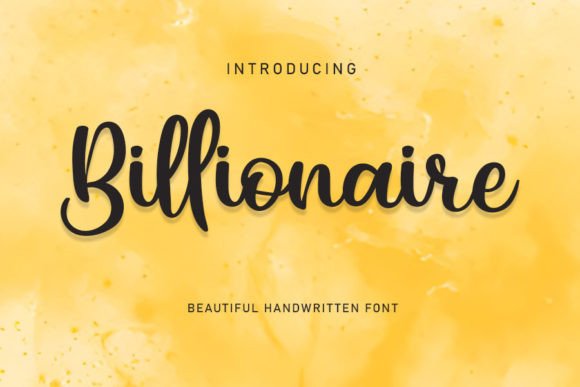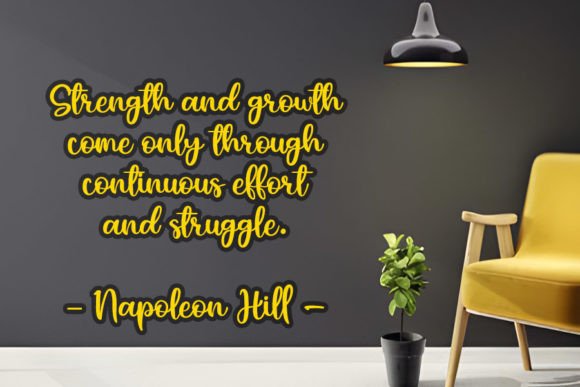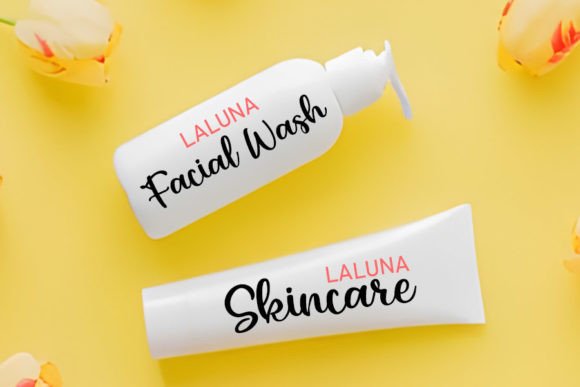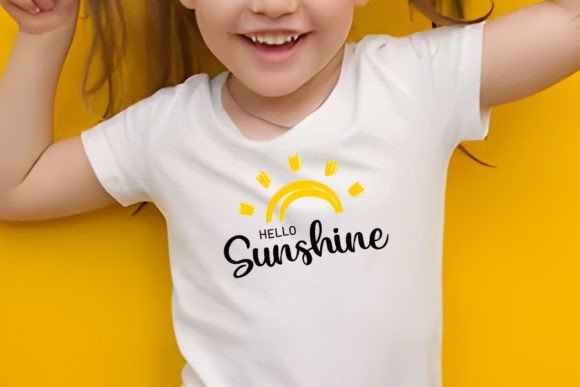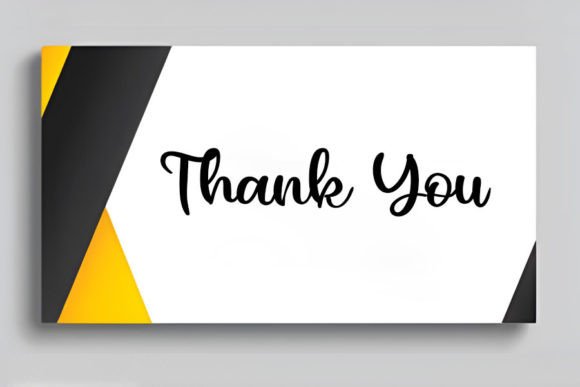
فونت Billionaire انگلیسی
| ⭐ توضیحات | Billionaire یک فونت دست نویس فوق العاده منحصر به فرد است. این فونت که استادانه طراحی شده است تا به یک مورد علاقه واقعی تبدیل شود، این پتانسیل را دارد که هر یک از ایده های خلاقانه شما را به بالاترین سطح برساند! این فونت دارای کد PUA است که به این معنی است که شما می توانید به راحتی به تمام حروف و swash ها دسترسی داشته باشید! |